Travis Scott convierte su cuerpo en tipografía en una extraordinaria perfomance que refleja sus palabras clave y su visión del diseño convertida en una experiencia visual, física y multisensorial.
El artista, compositor y productor nacido en Houston se mueve y contorsiona su cuerpo para transformarse en las 26 letras del alfabeto, y su original tipografía quedó plasmada en la tapa y el interior de la nueva edición de la revista de arquitectura y diseño Pin-Up Magazine.
De la A a la Z: la tipografía según Travis Scott
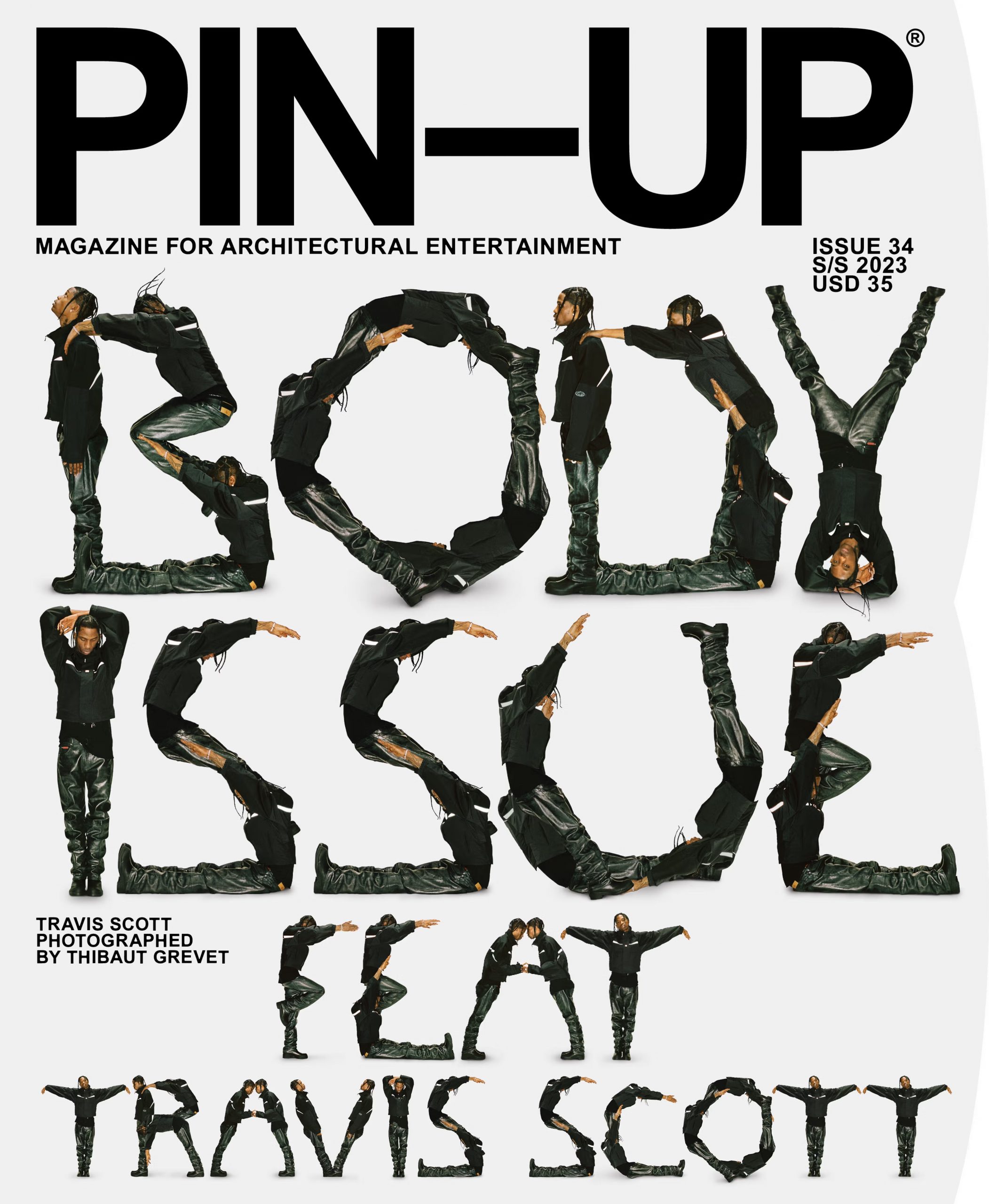
“Body Issue Feat Travis Scott” es el título de la producción protagonizada por la superestrella del rap que expresa su ABC del diseño empleando su propio cuerpo.
“El artista, compositor y productor nacido en Houston siempre ha superado los límites visuales y culturales -expresa el artículo de la extraordinaria producción- Crea universos multisensoriales para varios niveles de conciencia humana”.
10 pensamientos alfabéticos de Travis Scott
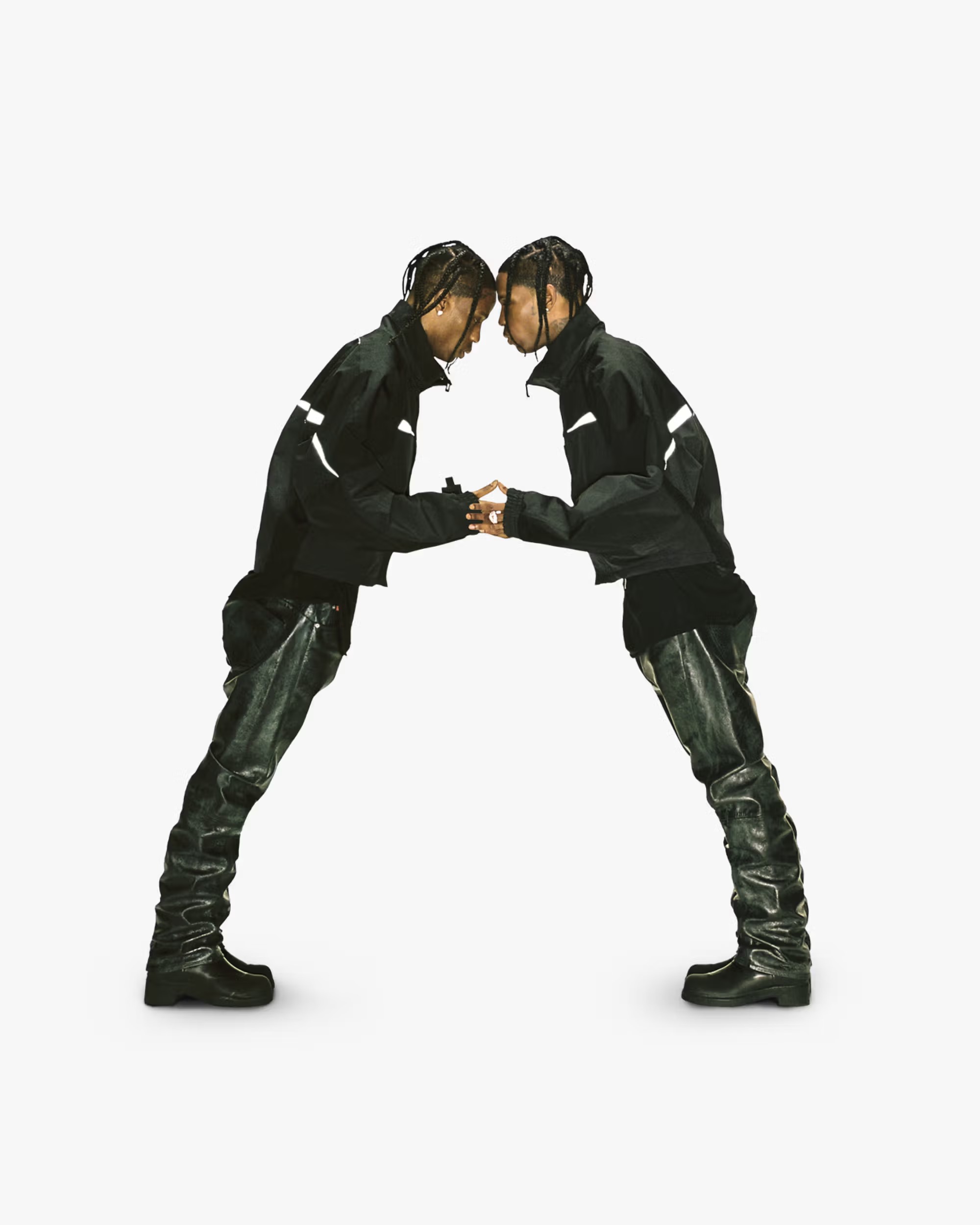
A de Arquitectura. “La arquitectura es mi verdadera pasión. Planeo solicitar plaza en el programa de arquitectura de la Escuela de Diseño de Harvard cuando termine con la música”.
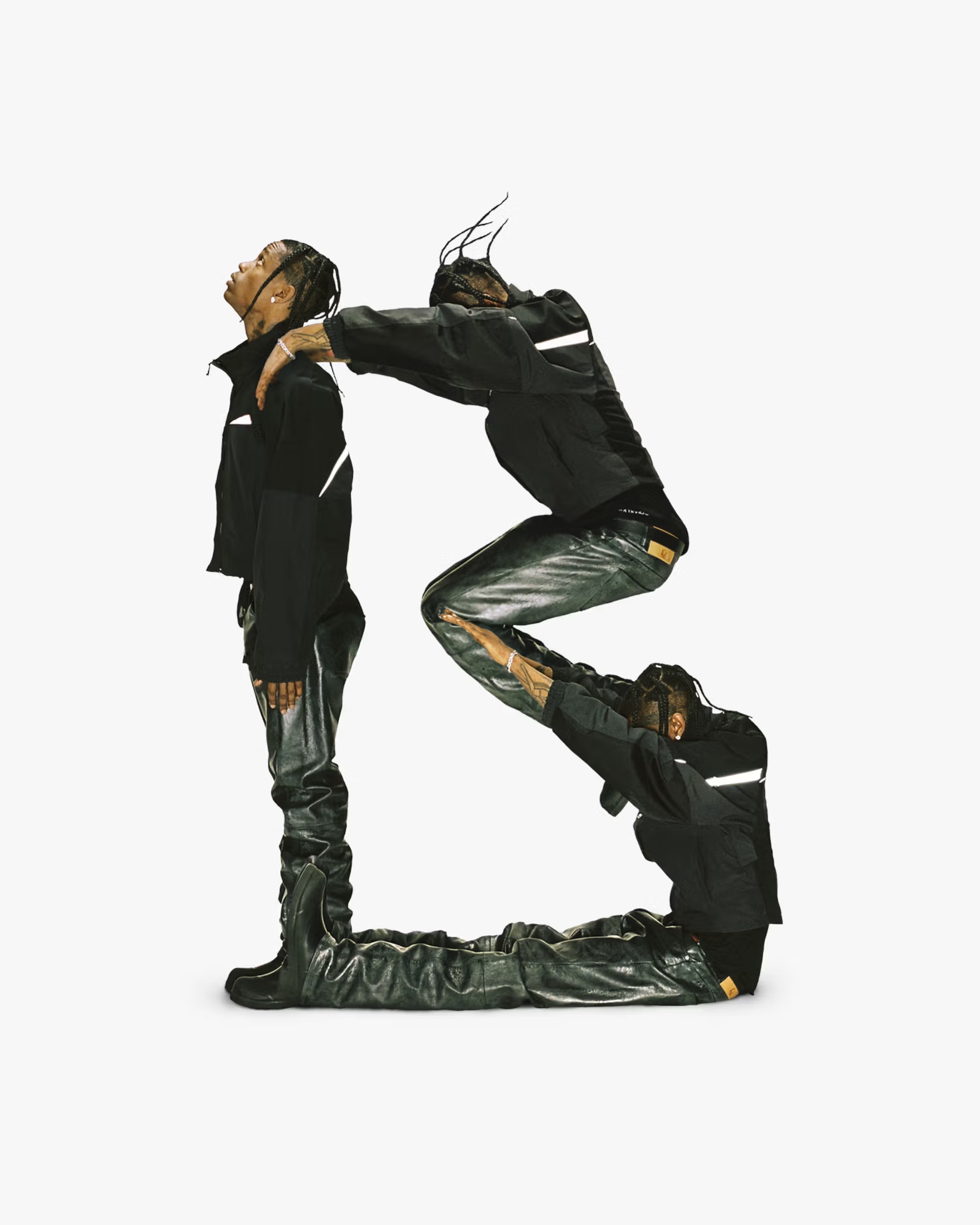
B de Brutalismo. "El brutalismo es sobrio. Así es como trato la música. Me gusta absorberlo todo y dejarlo caer. En la arquitectura brutalista encuentro consuelo en materiales crudos que cumplen una función”.
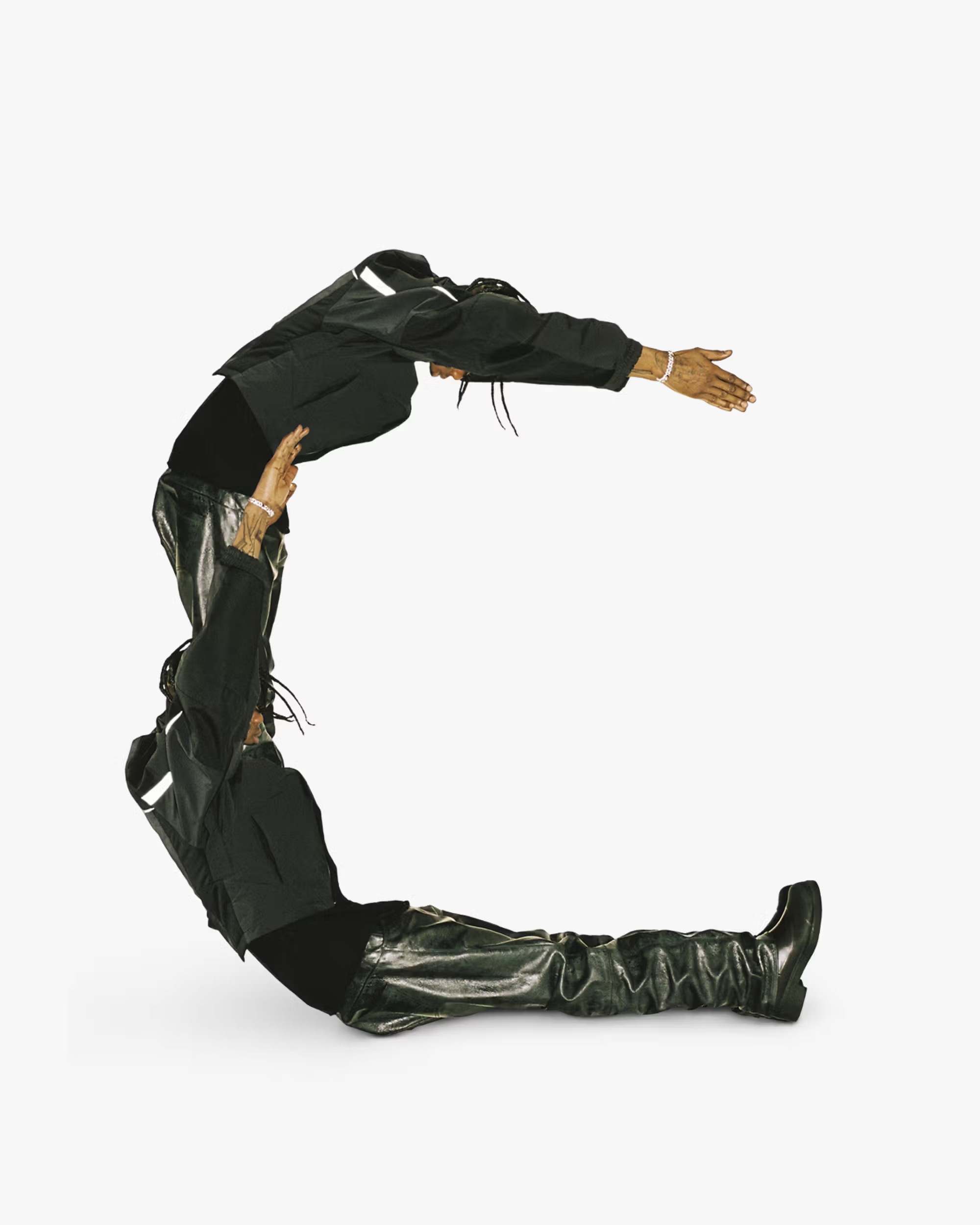
C de Coches. “Me gustan los coches. Tengo una colección muy exclusiva, con un Mercedes Benz G-Wagen cabriolet y un BMW M3 E30 de 1988. No busco coches nuevos. Busco personalidad; mis coches se adaptan a mis diferentes personalidades”.
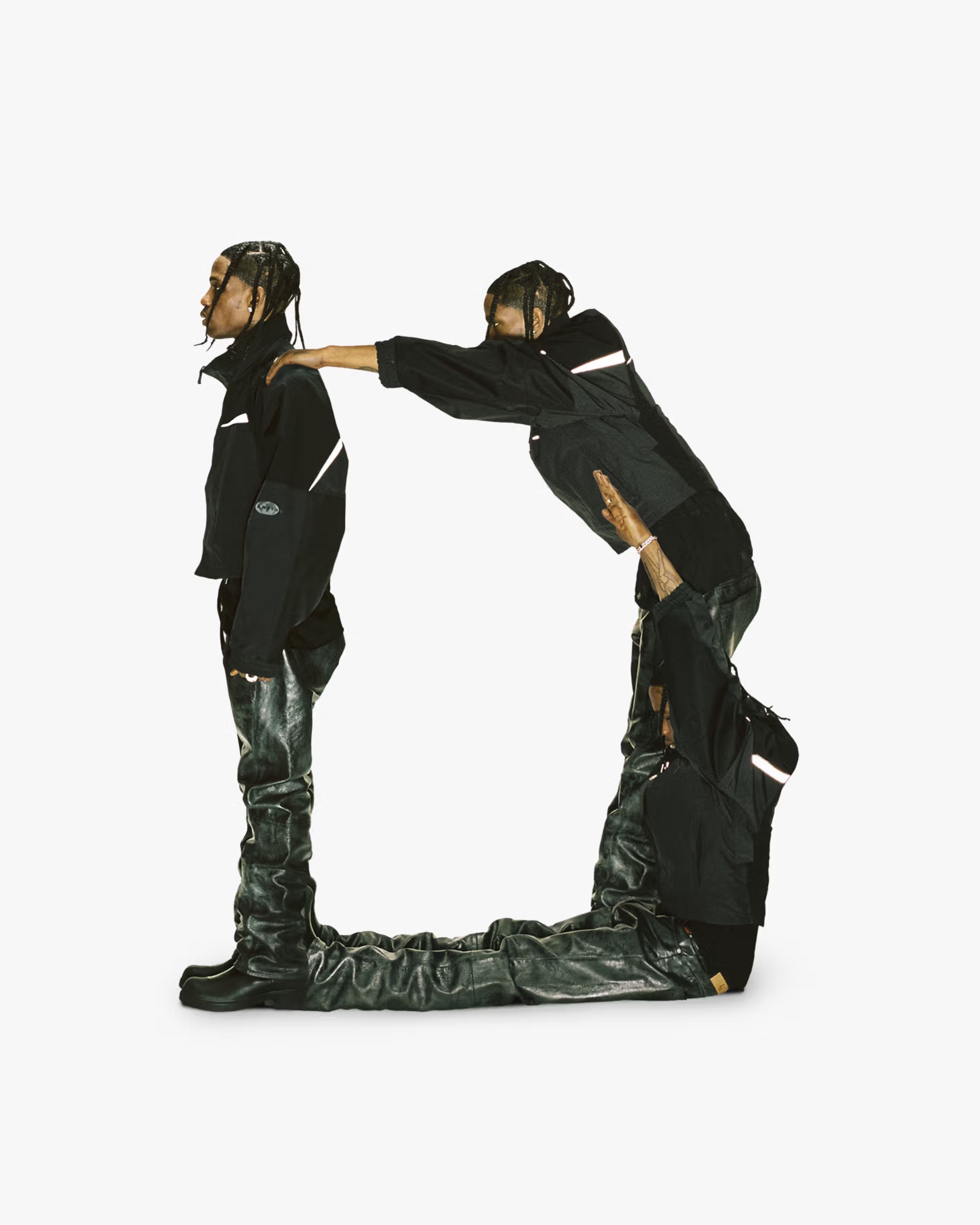
D de Dibujo. “El dibujo, y las artes visuales en general, son una de mis principales inspiraciones, especialmente al escribir música. Nada plasma las palabras en el bloc como el arte”.
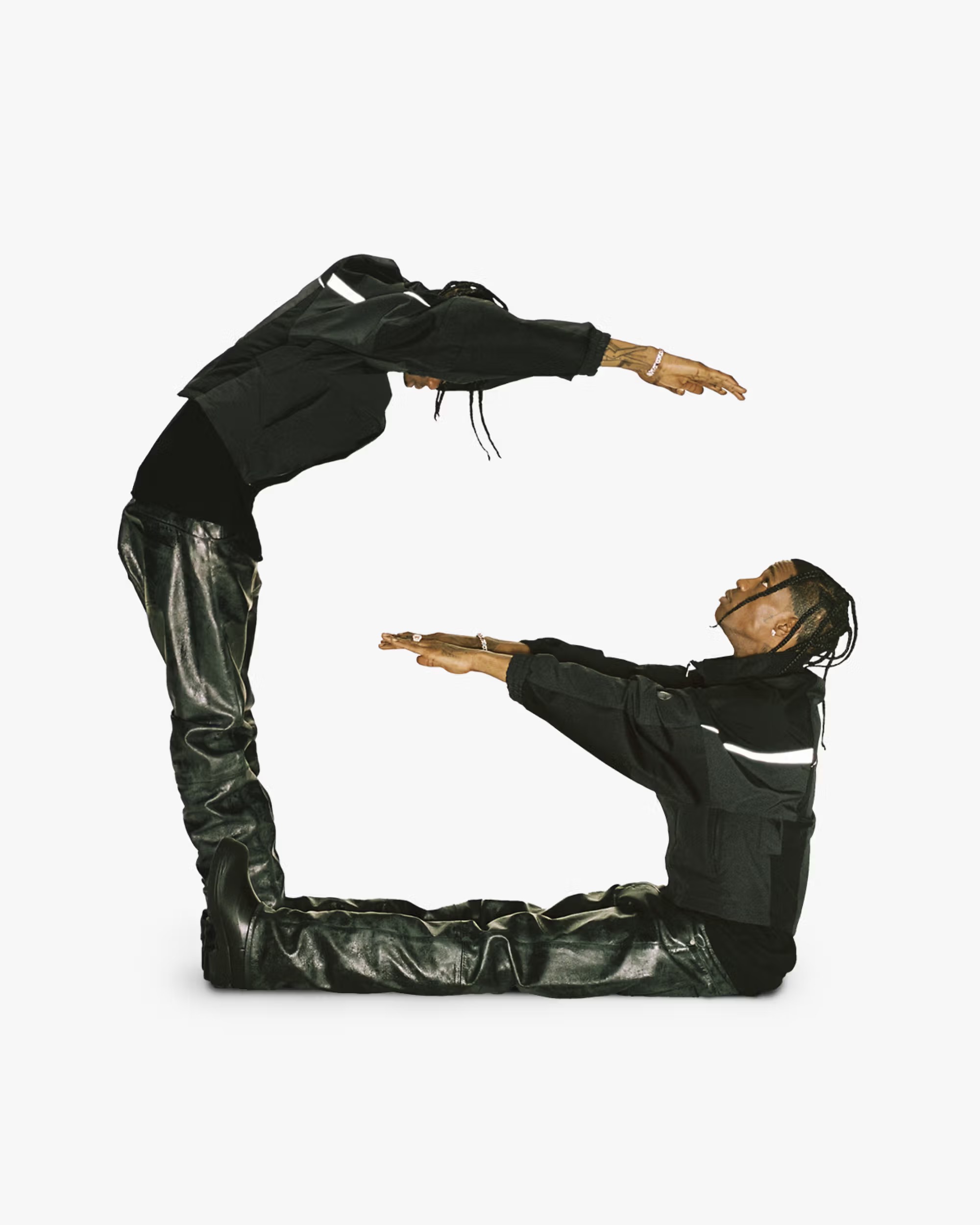
G de Diseño Gráfico. “Es una de mis verdaderas pasiones. El diseño gráfico implica mucho. Normalmente, uno se inclina por lo que refleja sus sentimientos o lo que representa su personalidad: los colores, las ilustraciones... todo influye. Entre mis logotipos estadounidenses favoritos están Campbell's Soup, Brillo y Frenchy's Chicken, un restaurante de Houston”.
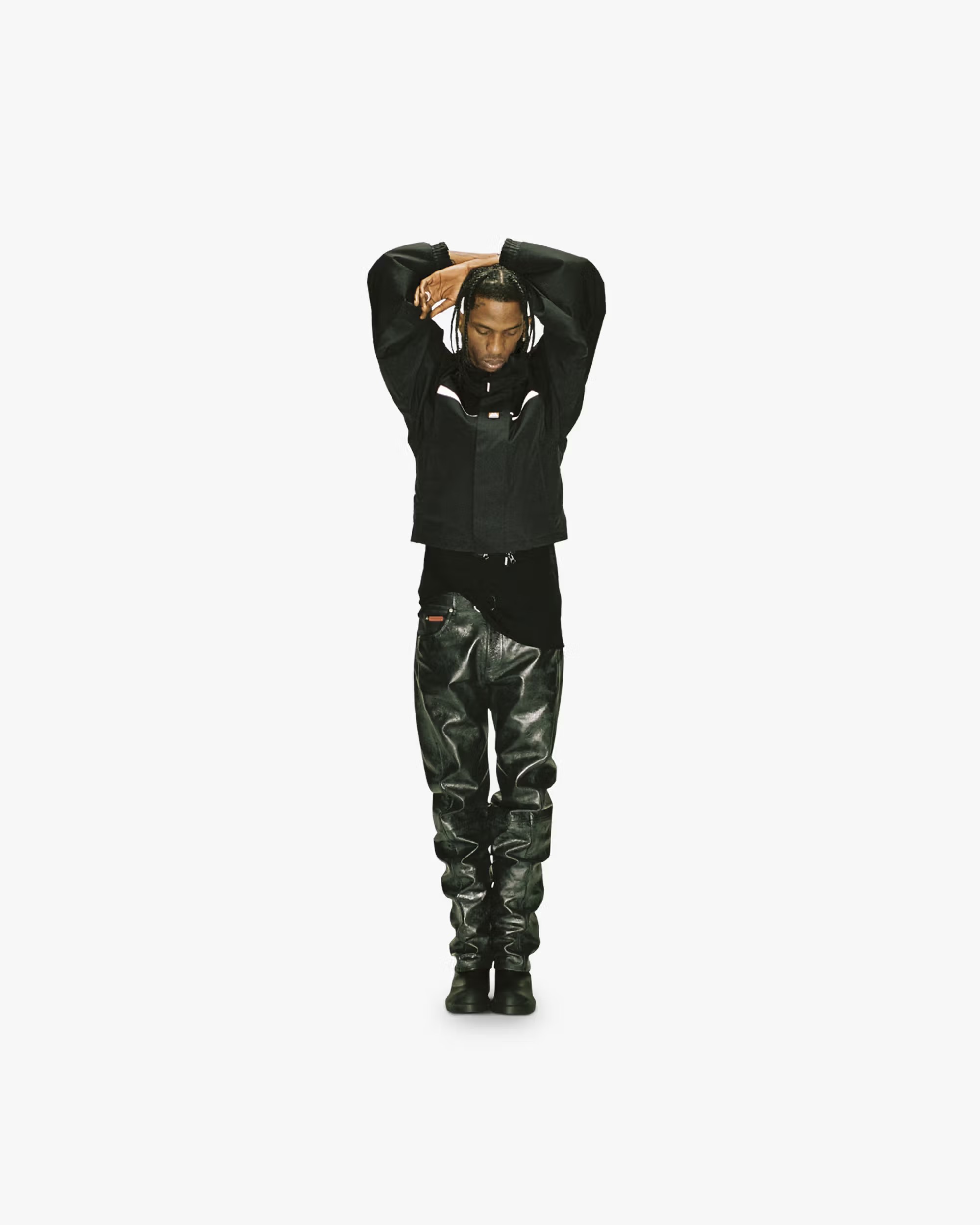
I de Impacto. “Generar impacto es divertido. Pero a veces la gente te da la vuelta a la pregunta de maneras extrañas. Hay gente que no entiende por qué eres influyente, y eso puede convertirse en un problema. La persona que más me impactó y me influyó en mis gustos fue Virgil (Abloh) Fue una verdadera inspiración”.
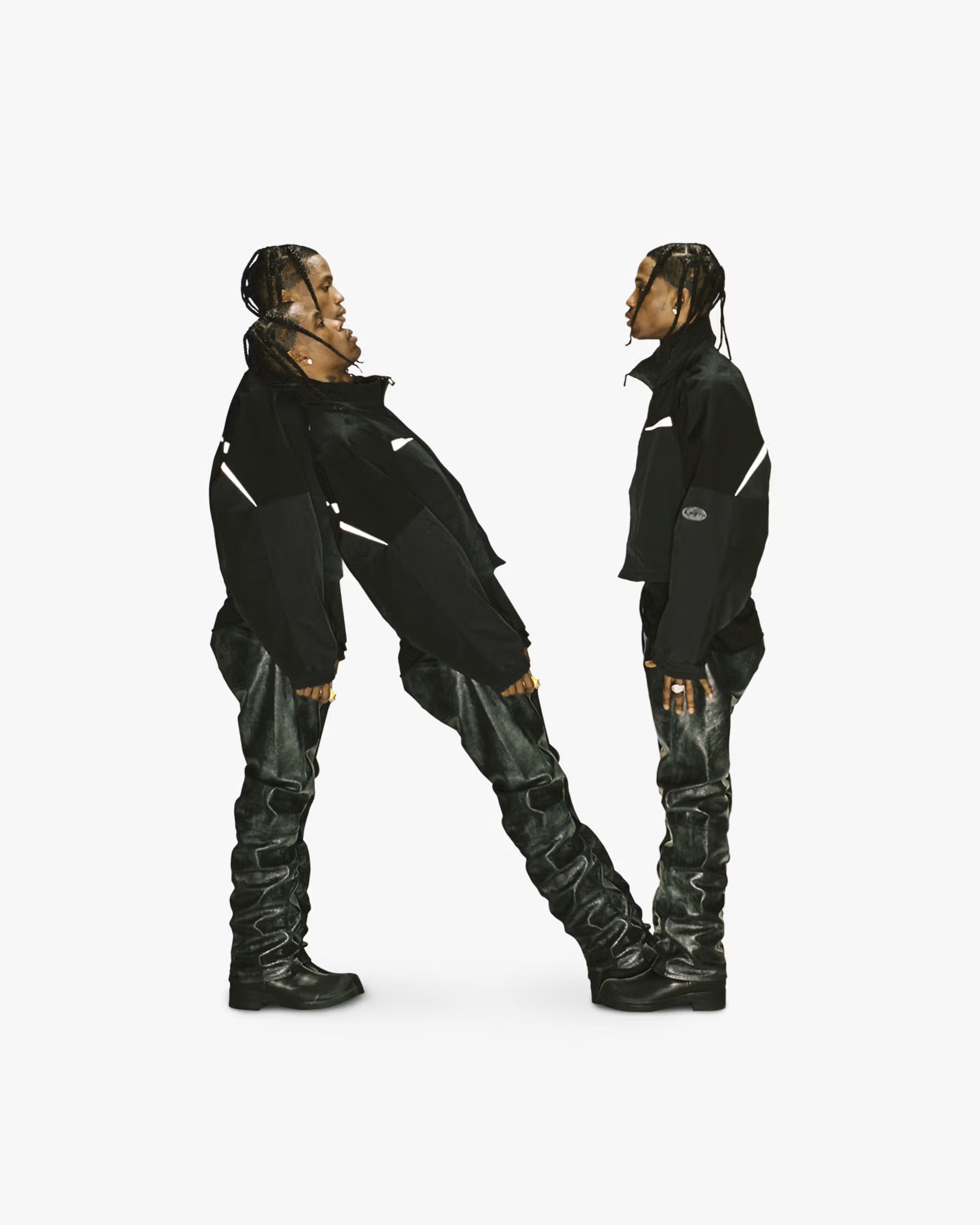
N de NASA. “De niño, siempre me hacía pensar en el espacio exterior. Tuvo un gran impacto en mí. El universo es mucho más grande que donde vivimos”.
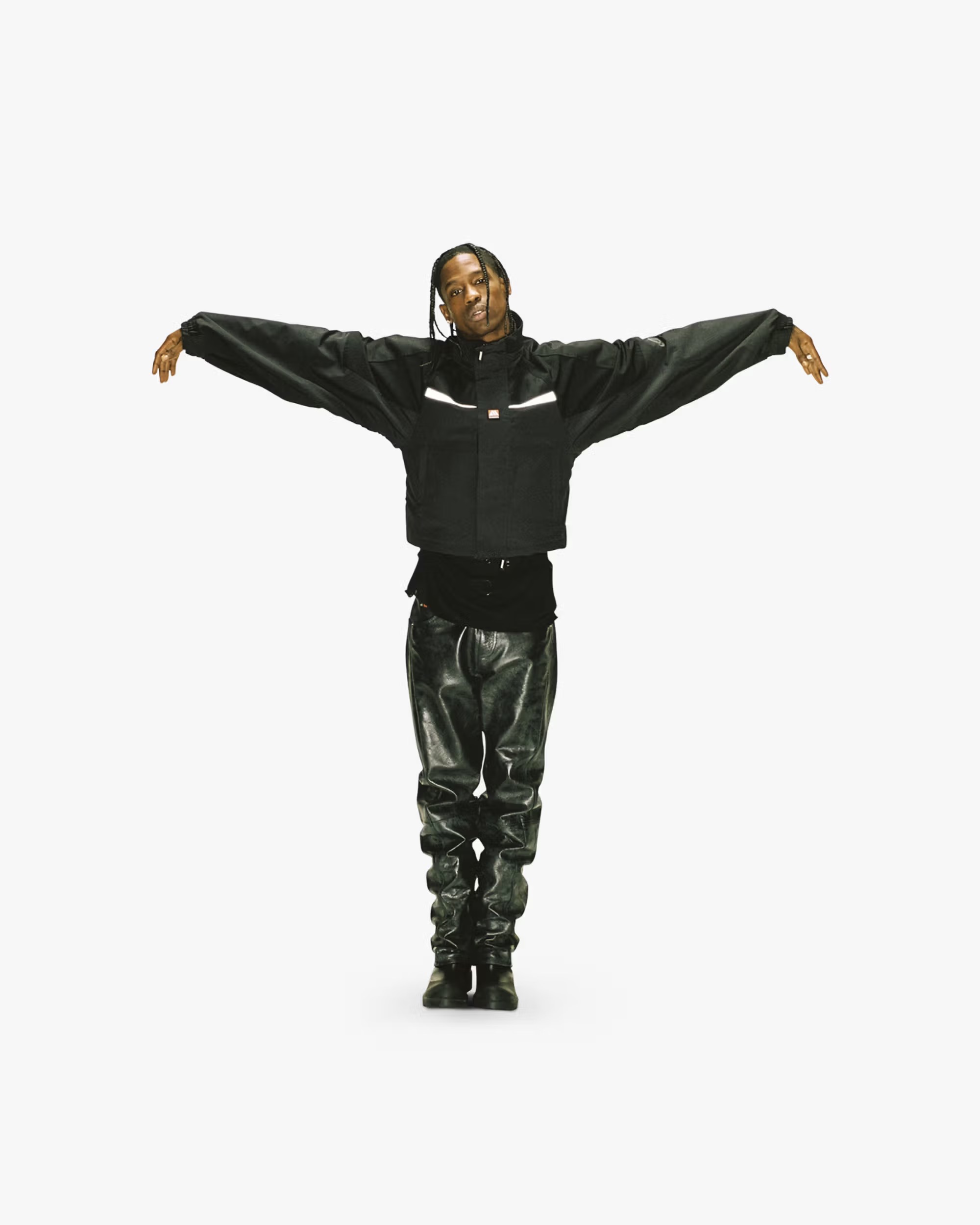
T de Tiempo. “El tiempo es atemporalidad”.
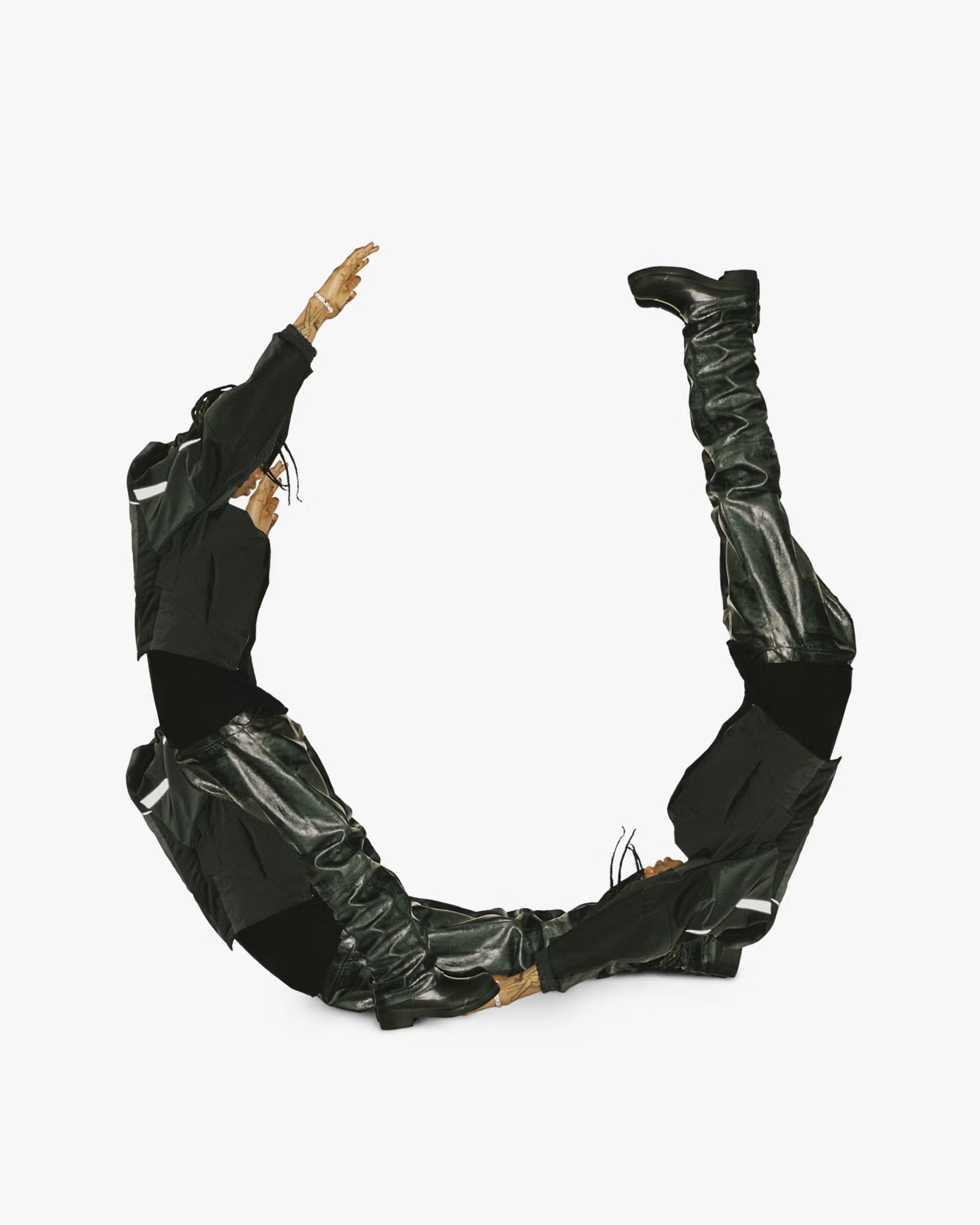
U de Utopía. “La utopía es algo que la gente considera inverosímil e inalcanzable, un estado mental perfecto. Pero la creas tú mismo. Hay gente que alcanza la utopía a diario (...) La gente necesita ver que la utopía es real”.
X de factor X. “Tener un factor X es clave (...) El factor X es difícil de conseguir. IKEA lo tiene. Es la idea de poder ofrecer algo accesible a la gente y que, a la vez, haga que su casa se sienta de otro nivel. Ese es el factor X. Un saludo a IKEA”.
De la A a la Z: el tributo de Travis Scott a Zaha Hadid
Z de Zaha Hadid. “Zaha Hadid fue revolucionaria”.